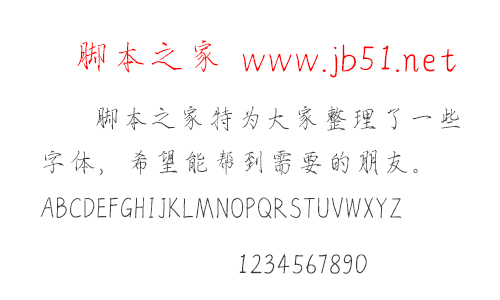
城南舊事字體是一款非常好看的硬筆手寫藝術(shù)字體,風(fēng)格比一般的字體更有特色,連貫字跡顯得干練而不凌亂,清新簡明,具有很好的視覺感,適合應(yīng)用于藝術(shù)設(shè)計、平面宣傳設(shè)計、網(wǎng)頁設(shè)計,書法字帖等領(lǐng)域,歡迎喜歡城南舊事字體的朋友前來下載使用。